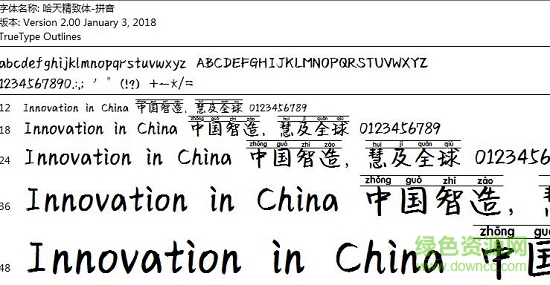
小米精致拼音字體
精致拼音體ttf是一款非常有特色的拼音字體,比起一般的拼音體字體,這款字體為拼音加入了兩條橫線,格外的與眾不同,有喜歡這款字體的朋友歡迎下載使用!
精致拼音體ttf簡介
精致拼音體ttf是一款個(gè)性十足的中文字體,這款字體漢字采用手寫類型的黑體字體打造,每個(gè)漢字的上方都為你準(zhǔn)備了拼音,看上去非常的有意思!